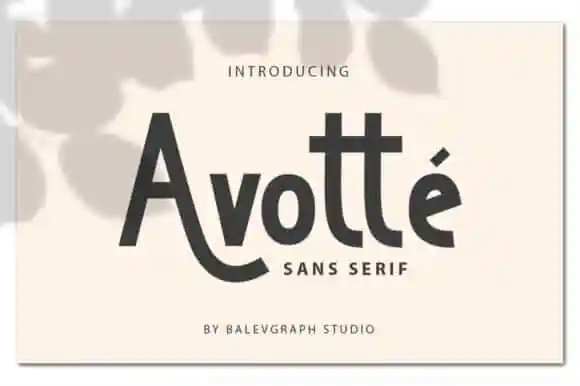
Avotte Sans Serif Font – Download Grátis
A Avotte Sans Serif é uma fonte criada pela Balevgraph Studio que captura a essência do tipo sans serif com um charme inegável e personalidade vibrante. Suas linhas elegantes e limpas se combinam perfeitamente para criar designes engraçados, práticos e criativos, tornando-a uma escolha perfeita para seus projetos de marca e comunicação visual. Esta fonte é ideal para uma variedade de usos gráficos: rótulos inspiradores, material de marca, cartões de visita, headlines, blogs, logotipos, artefatos da Cricut e até mesmo postais. Combinada com a Avotte, você pode adicionar um toque único a qualquer projeto, tornando-o ainda mais impecável.